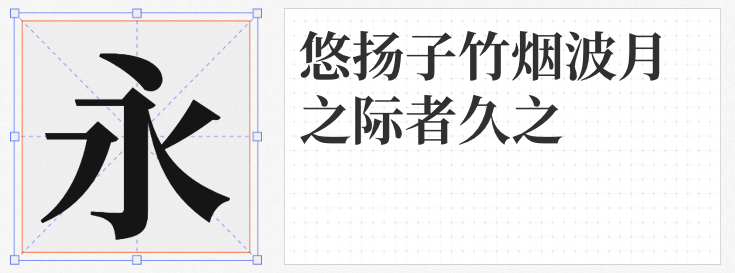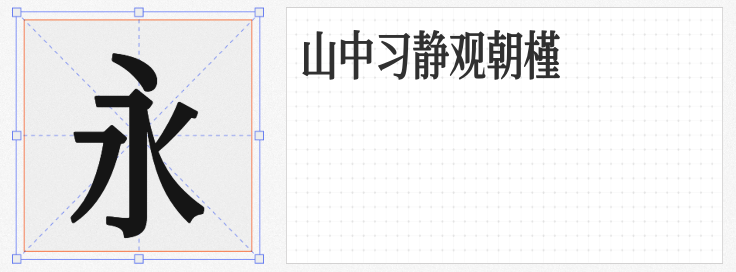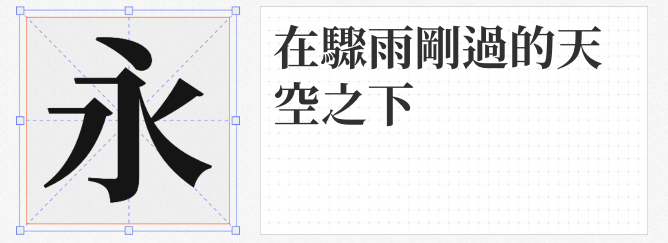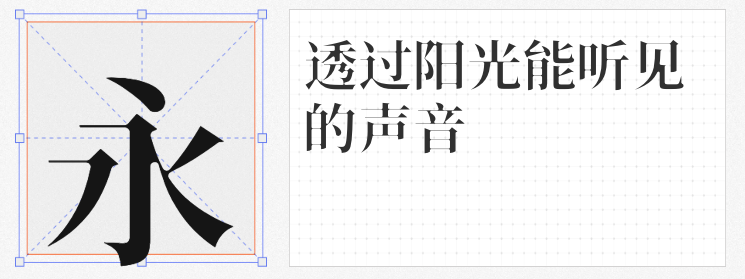
在设计的广阔天地里,宋体以其独特的韵味与实用性,成为众多设计师的心头好。今天,我们精心挑选了四款免费商用的宋体字体,它们不仅风格各异,更能在不同设计场景中大放异彩。
1. 香萃潮汐宋 W15
这款字体以其圆润的笔画和巧妙的粘连设计,营造出一种柔和而富有美感的视觉体验。横细竖粗的对比,使得文字在保持古典雅韵的同时,又不失清新明快。无论是书刊印刷、广告设计,还是包装设计,香萃潮汐宋都能完美融入,甚至在恐怖题材中,其笔画间的朦胧感与视觉张力,也能为作品增添一抹神秘色彩。
2. 昭源宋体 Bold
源自思源宋体香港版的精心修改,昭源宋体在保留宋体基本特征的同时,对部分字形进行了优化调整,使其更加符合繁体中文地区的阅读习惯。尽管其设计初衷在于解决字形陌生问题,但独特的字形处理,也为设计作品带来了一抹别样的风情。
这款字体基于思源宋体的开放原始码,巧妙融合了韩文版本字符与繁体中文置中标点,使得排版更加贴近传统印刷体风格。对于追求古典韵味与现代设计融合的设计师而言,源样明体无疑是一个不可多得的选择。
结合了黑体与宋体的精髓,寒蝉端黑宋以其独特的横向加粗设计,打破了传统宋体的束缚。既有黑体的粗壮有力,又不失宋体的优雅饰角,使得这款字体在硬朗与雅致之间找到了完美的平衡点。
这四款免费商用宋体字体,各具特色,无论是追求古典雅韵,还是现代创新,都能在其中找到满意的答案。